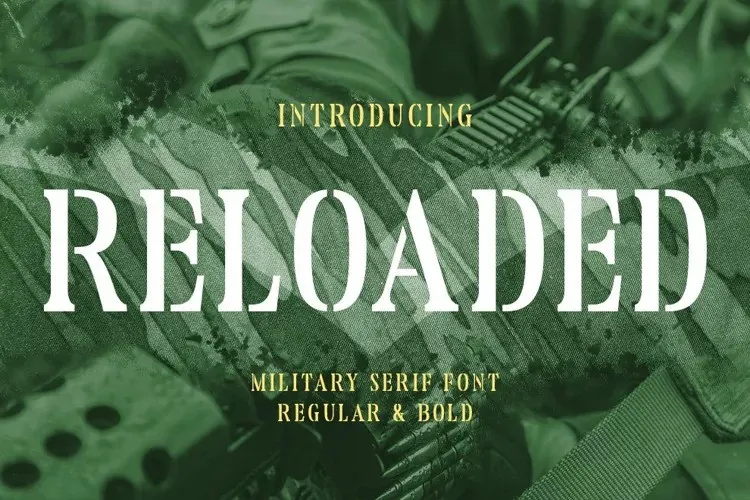
Reloaded Font – Fonte Grátis
Reloaded Font
Esta fontes serif foi criada pelo designer 99designs para Almarkhatype. Com seu estilo elegante, forte e distintivo, esta fonte serifa é perfeita para criar materiais que precisam de um toque sofisticado. Ela se destaca não apenas como uma opção adequada para projetos profissionais, mas também como a escolha ideal para criações mais criativas e casuais. É perfeitamente apropriada para trabalhos onde é necessário um estilo tradicional, como posters militares, scrapbooking, cartas de convite, estilos de vida, embalagens, botões, pingentes, presentes natalinos e até mesmo impressão em tecidos. A sua qualidade faz dela uma opção versátil para muitos projetos gráficos que valorizam um design serif tradicional, sem comprometer a elegância ou facilidade de uso.